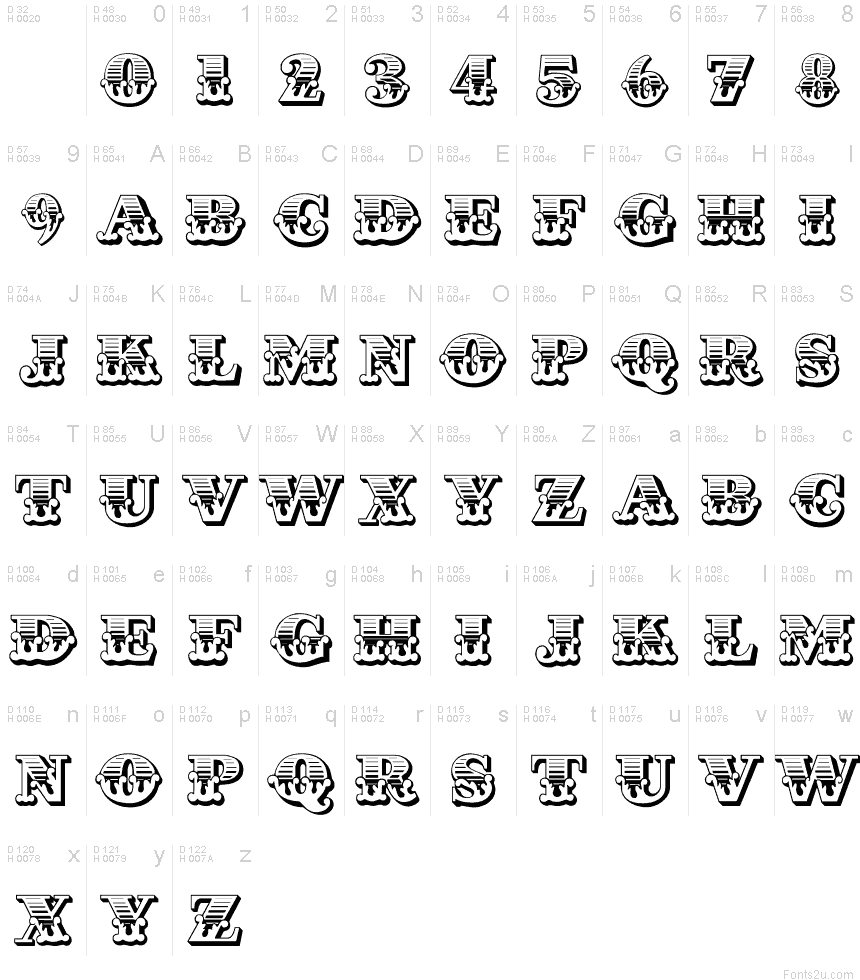
A fonte Cast Iron, da West Wind Fonts, canaliza o estilo arrojado das feiras antigas, com formas robustas, interiores listrados e curvas fluidas que parecem fundir-se na base. Os contornos pesados e a sombra integrada conferem a cada palavra uma sensação de solidez e metalurgia, lembrando sinalizações de máquinas antigas ou letreiros de parques de diversões.
Esta fonte gratuita funciona particularmente bem em cartazes, logotipos vintage, embalagens, títulos de eventos, banners, capas de livros ou álbuns e elementos gráficos para jogos ou escape rooms. Cast Iron sobressai especialmente em tamanhos grandes, onde as suas listas e ornamentos podem respirar. Combina perfeitamente com uma fonte sem serifa simples para textos longos, garantindo a legibilidade do layout.